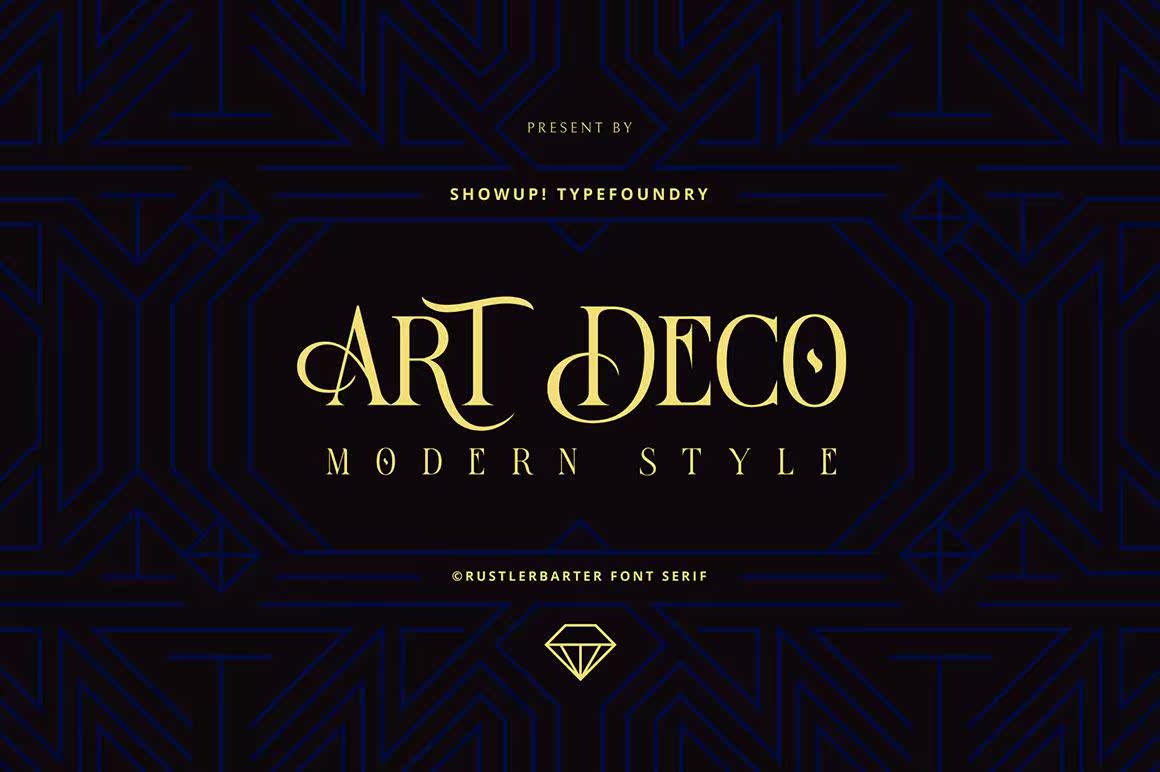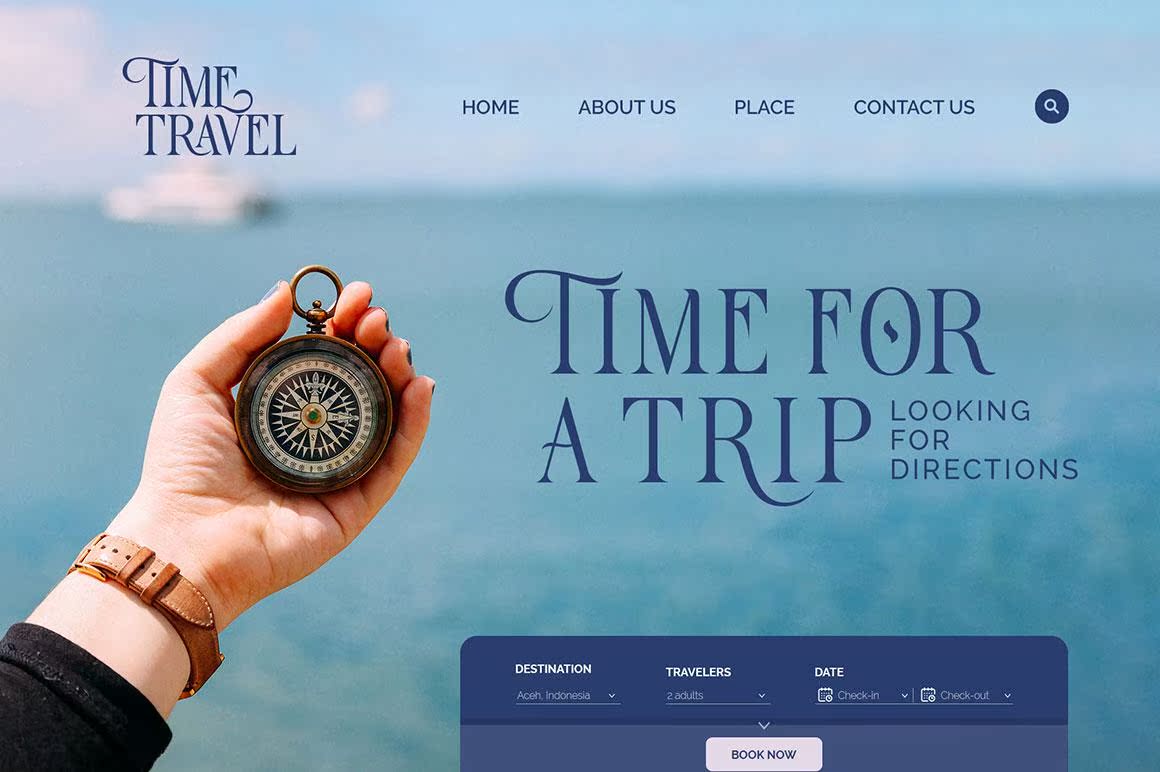
RustlerBarter®是一款受ArtDecora启发而设计的精美展示品。它完美地体现了现代和简约的美学风格。内容包括特殊大写字母、可选字符和美丽的插图。此外,该内容在精美的标志设计、包装、,或装饰牌。RustlerBarter®是一款受ArtDecora启发而设计的精美显示器。它完美地体现了现代和简约的美学。内容包括特殊大写字母、可选字符和美丽的装饰。此外,该内容在装饰牌的设计、包装或装饰牌方面都是完美的。